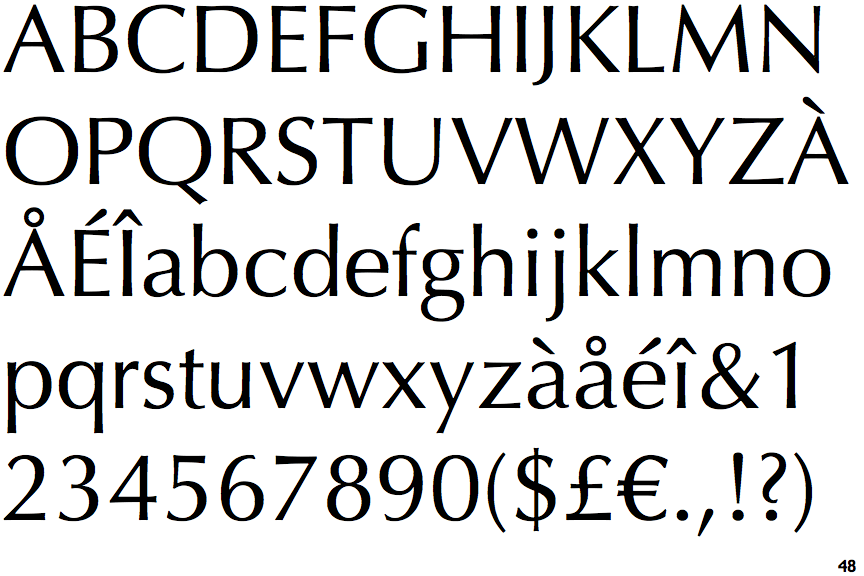
Type 1 Schrift identisch mit OTF-Version? - Hier: OptimaBQ vs. Optima Pro
ich habe mir für die Beschriftung eines Grabkissens in 2019 bei Linotype einen Schriftschnitt der Optima gekauft. Die Indesign-Datei und die Schrift sind leider auf einem Rechner, der gecrasht ist und die Daten habe ich noch nicht gerettet. Anhand einer alten PDF-Datei sehe ich als Schrifteninfo OptimaBQ Type 1.
Die Beschriftung muss nun leider ergänzt werden und das soll natürlich die identische Schrift sein. Bei Linotype konnte ich die Schrift erneut herunterladen, jetzt als OTF und mit dem Namen OptimaPro.
Kann ich davon ausgehen, dass die Schriften identisch aussehen oder ist mit kleinen Unterschieden zu rechnen? Wie sind eure Erfahrungen?
Der Font wird nicht vollkommen identisch aussehen/laufen, es ist aber natürlich vom grundsätzlichen Charakter her die gleiche Schriftfamilie. So oder so, der Wechsel zu OpenType-Schriften ist aber ohnehin fällig. Type 1 ist ein veraltetes, nicht mehr voll unterstütztes Format und Berthold gibt es als Schriftanbieter auch nicht mehr.
Bei kleineren Einzelprojekten, wo jetzt also nicht zum Beispiel 600 Buchseiten komplett anders umbrechen, sollte so ein Schriftwechsel nicht so problematisch sein.
Die Optima von Hermann Zapf gibt es auch in einigen Schnitten frei als URW-Classico.